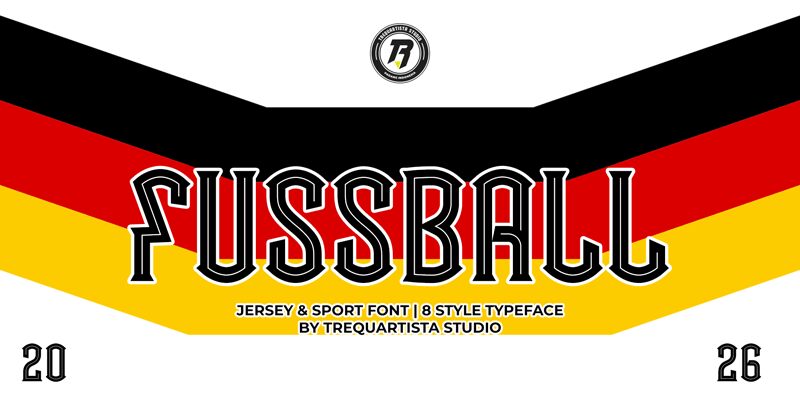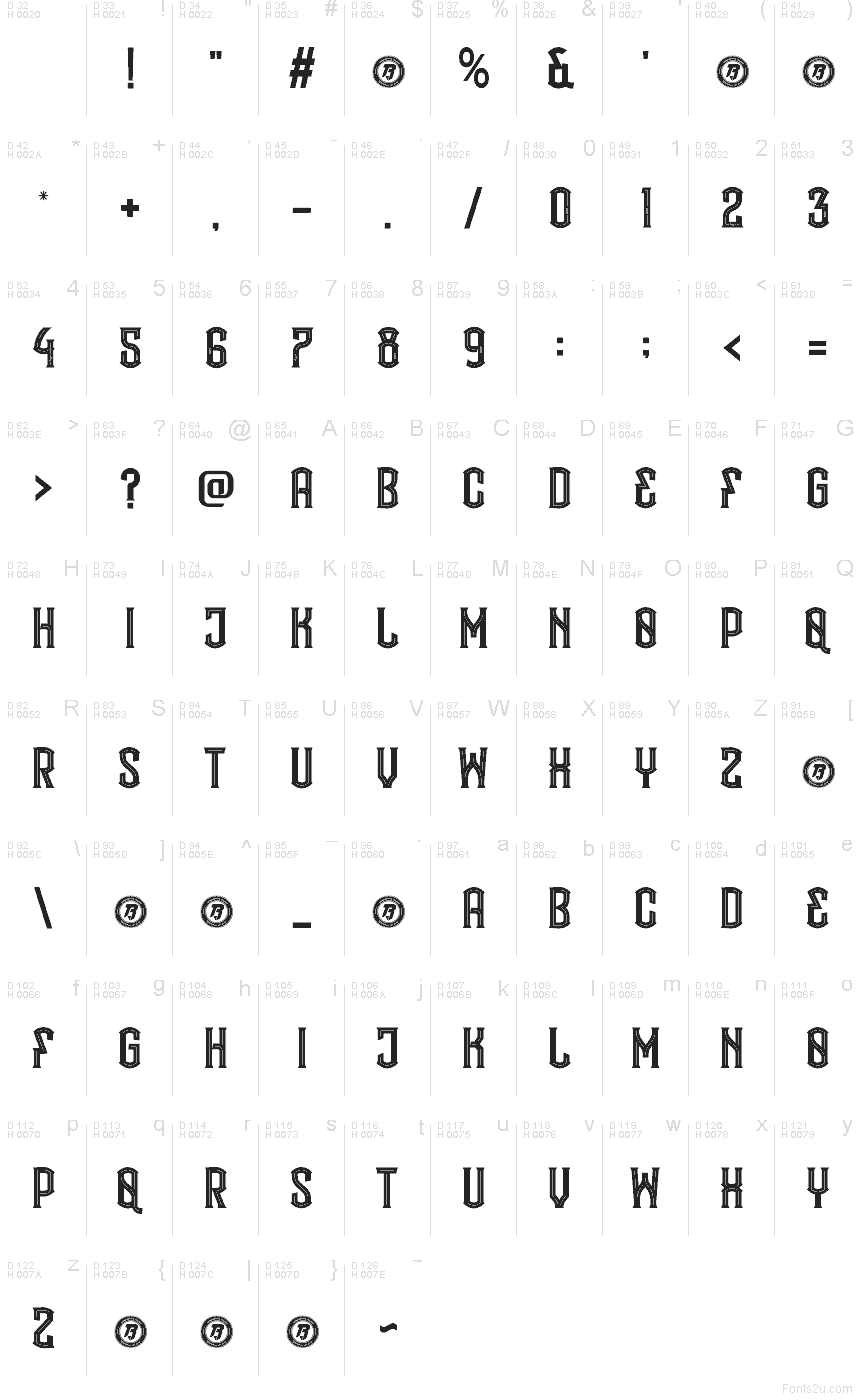
Fussball, de Trequartista Studio, es una tipografía gótica moderna y gratuita que evoca el estilo de los antiguos rótulos de clubes de fútbol y estandartes cívicos. Sus mayúsculas combinan arcos y uniones puntiagudas propias del estilo gótico con una silueta amplia y robusta; gracias a su línea interior, las letras mantienen un aspecto formal y equilibrado.
Es perfecta para branding deportivo, titulares de pósteres, bufandas de equipos, etiquetas, letreros de pubs y tarjetas de título donde ese toque heráldico aporta solemnidad a las palabras. Al ser gratuita, también es ideal para textos cortos, monogramas y diseños de merchandising, ya que sus esquinas biseladas y su estilo de doble línea confieren a las palabras una presencia contundente, similar a la de una insignia.